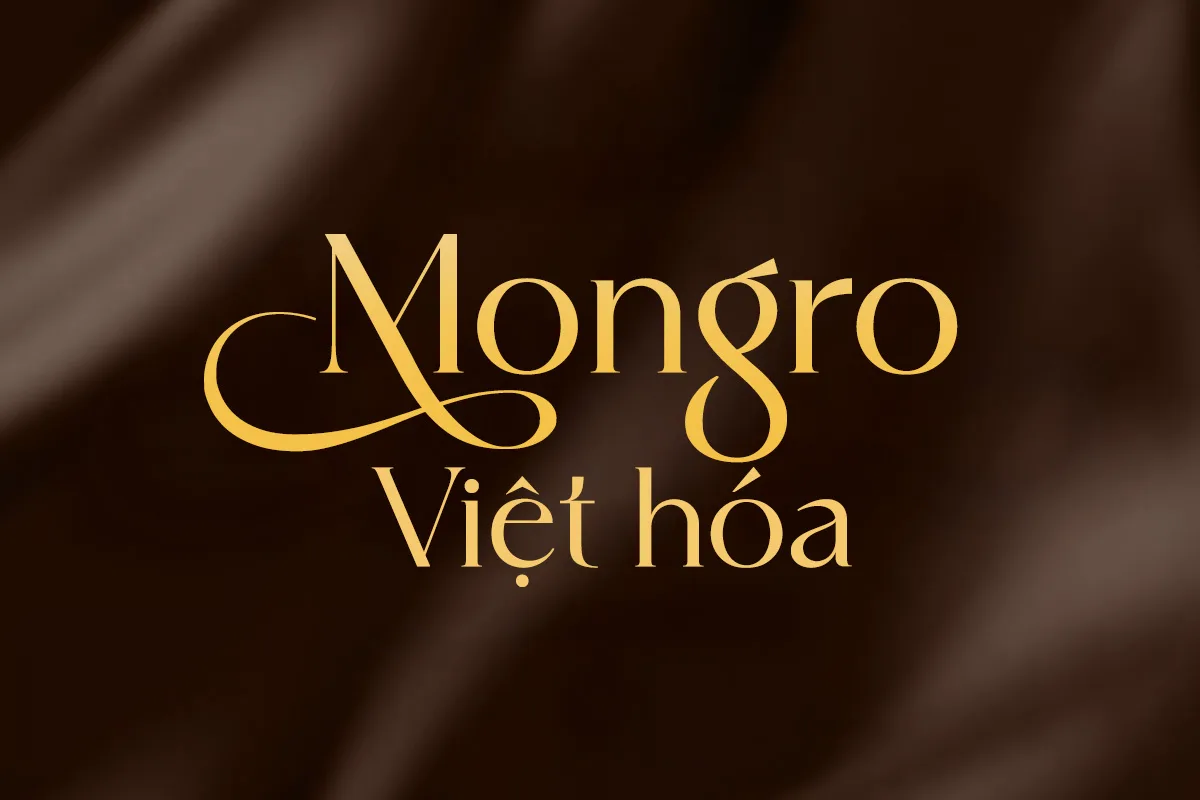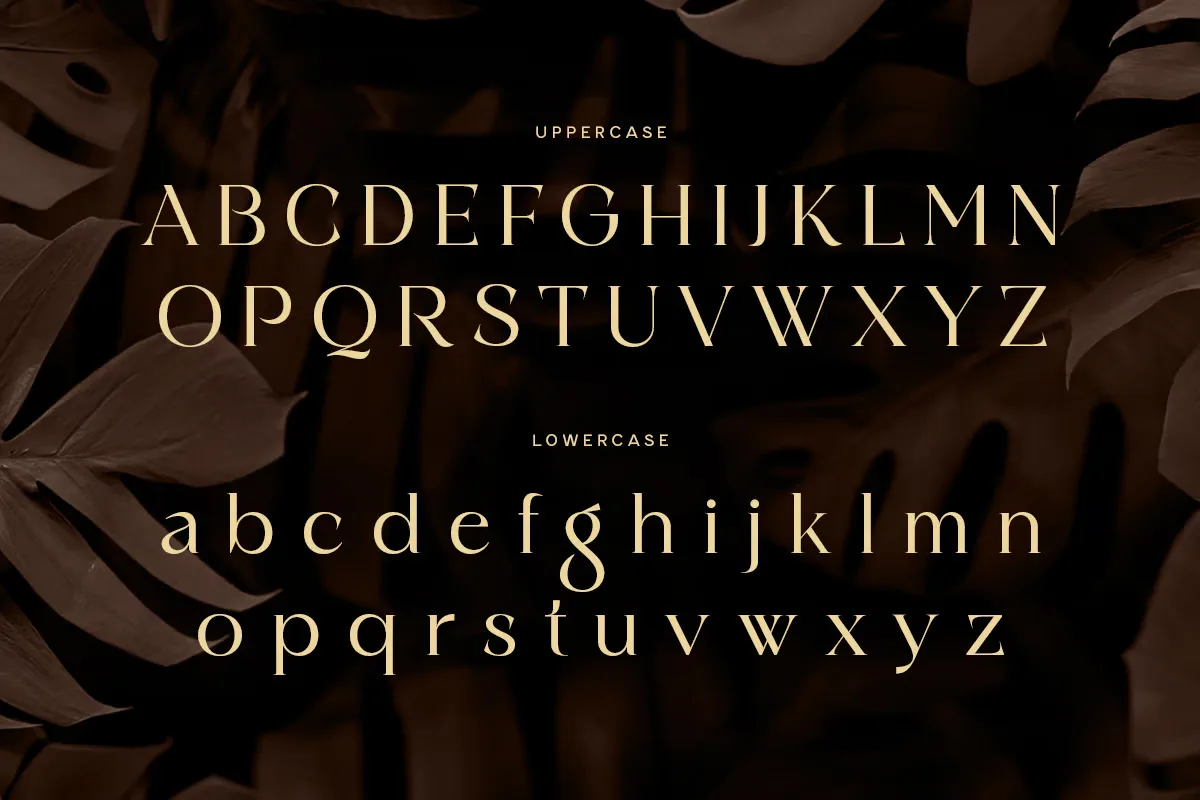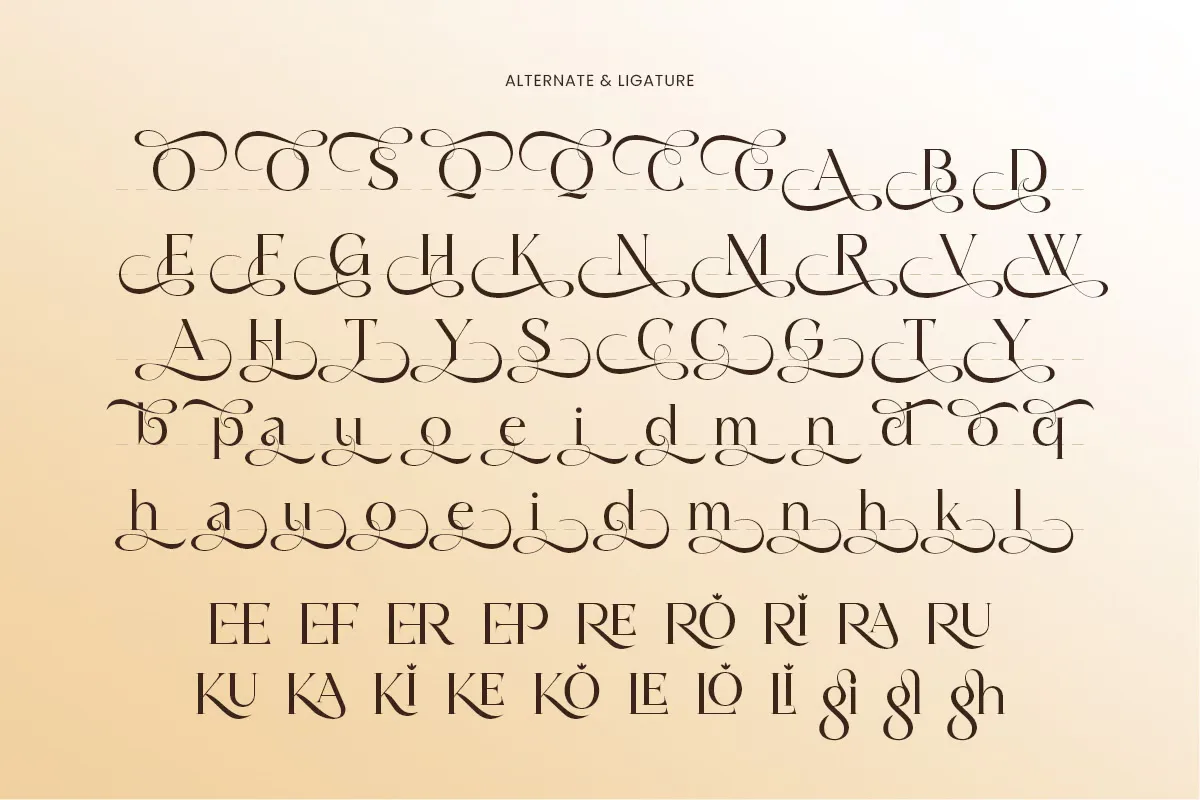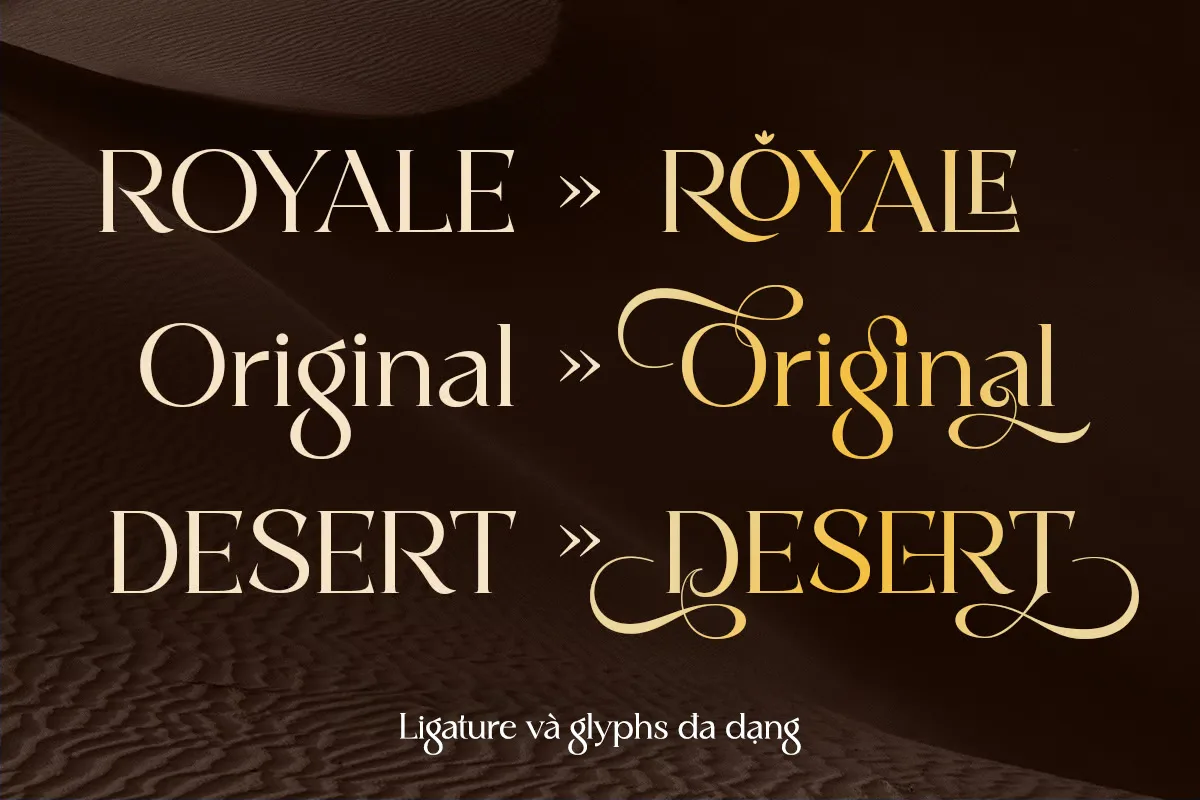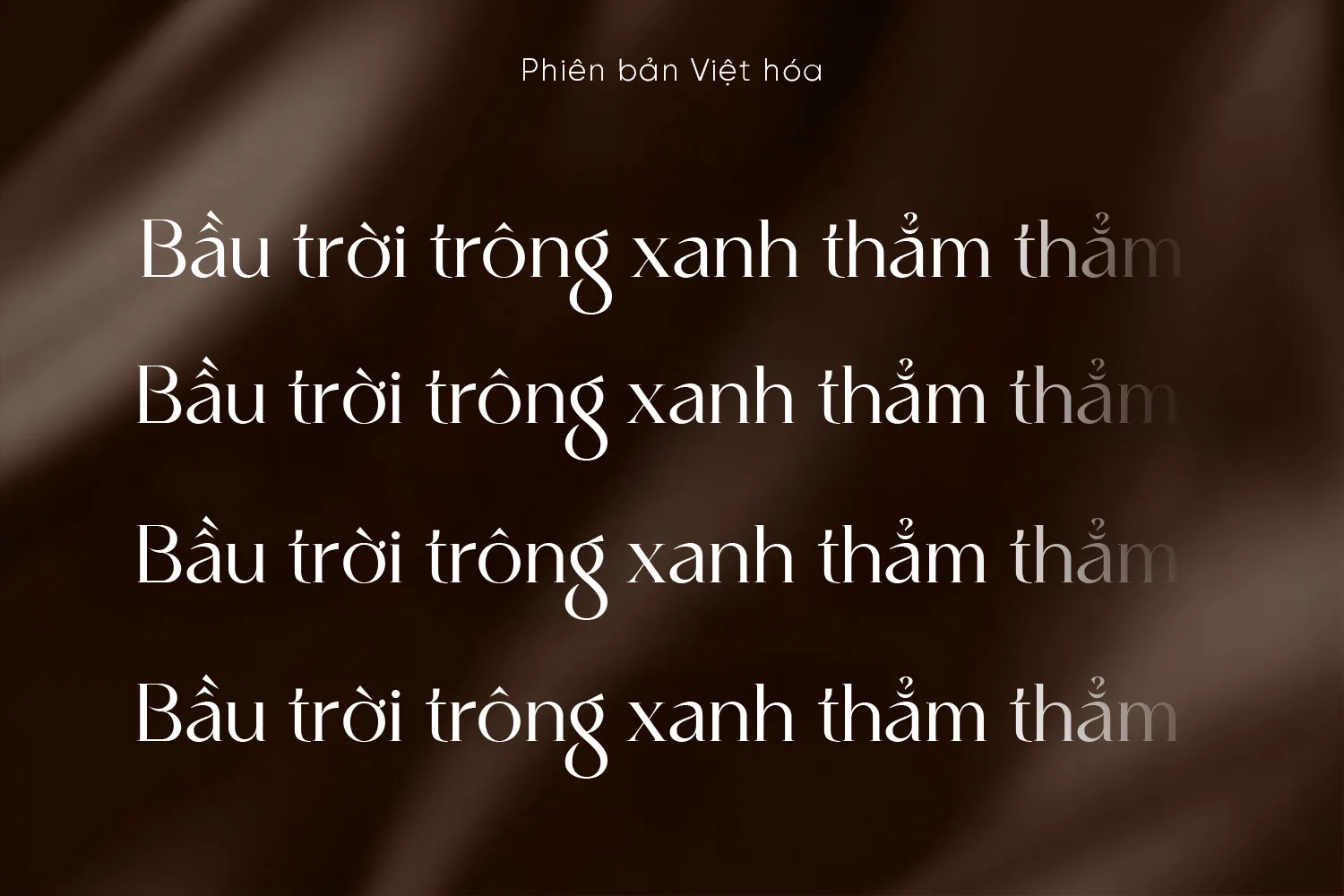
DVN Mongro – Font hiện đại pha chút cổ điển đầy tinh tế với nhiều biến thể uốn lượn đẹp mắt
DVN Mongro là phiên bản Việt hóa chỉn chu của một kiểu chữ mang phong cách serif hiện đại, kết hợp giữa vẻ cứng cáp của cấu trúc chữ và những đường cong tinh tế tạo nên sự cân bằng thị giác hoàn hảo. Với các nét gãy gọn, chân chữ thanh mảnh nhưng không kém phần mạnh mẽ, DVN Mongro phù hợp cho các dự án cần sự lịch thiệp, cổ điển nhưng vẫn thời thượng, như thiết kế thương hiệu, bìa sách, bao bì cao cấp hay tạp chí nghệ thuật.
Bộ font hỗ trợ đầy đủ tiếng Việt, giữ nguyên các đặc điểm thiết kế gốc và được tinh chỉnh để đảm bảo độ tương thích cao trong môi trường thiết kế chuyên nghiệp. Nếu bạn đang tìm kiếm một kiểu chữ sang trọng, trang nhã nhưng không quá cầu kỳ, DVN Mongro chính là lựa chọn lý tưởng để tạo dấu ấn khác biệt trong từng dự án.